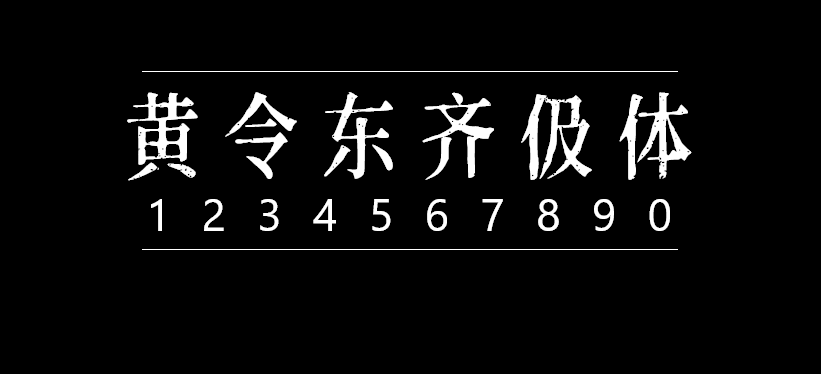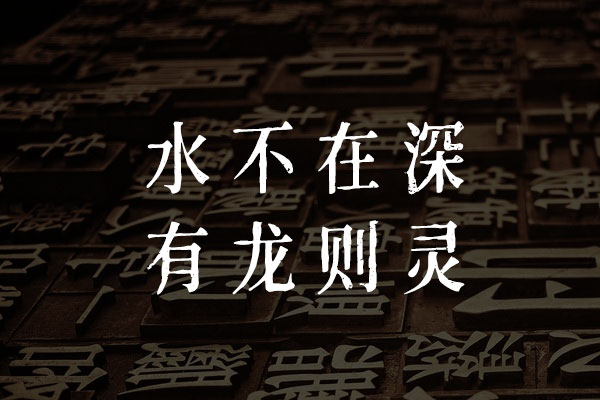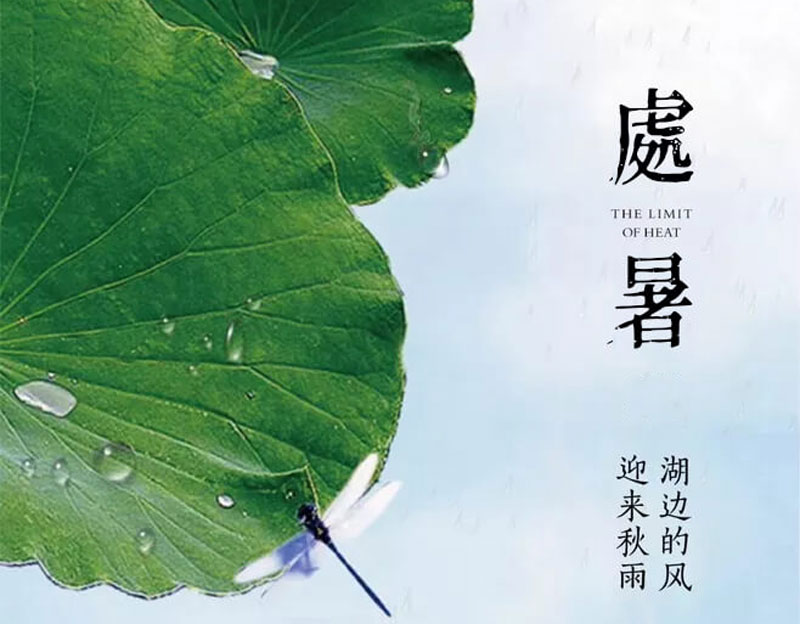
黄令东齐伋体
黄令东齐伋体(之前被误命名为《凌东齐伋体》,特此更正),一款可以媲美康熙字典体的免费商用字体!可以免费商用!黄令东齐伋体摘自明代木版印刷书籍《凌閔刻本》,采用半自动计算机视觉和OCR制作而成的一款字体。其笔画风格书法特征浓郁,比常规的明朝体更具韵律感,富有人文气息。黄令东齐伋体非常适宜用于需要展现人文感、手作感、古拙感的场景。 黄令东齐伋体(QIJIFALLBACK Regular)是基于思源宋体改造而来,所以对中文汉字很全,无论是简体还是繁体都基本上不缺字! 依据SIL Open Font License 1.1授权协议,可以用于任何用途,包括免费商用。